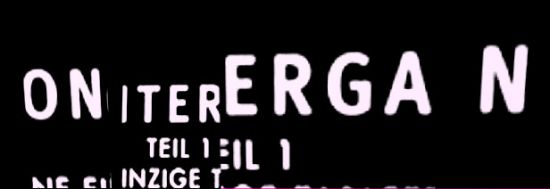
Titelschrift vom Film "Contergan" gesucht
Leider habe ich das nur als Screenshot in dieser miesen Qualität, und dann noch nicht mal ganz. Welche Schrift ist das?
Wenn ich das "G" und das "E" anschaue sehe ich da zwei verschiedene Fonts… welche weiß ich grad auch nicht.